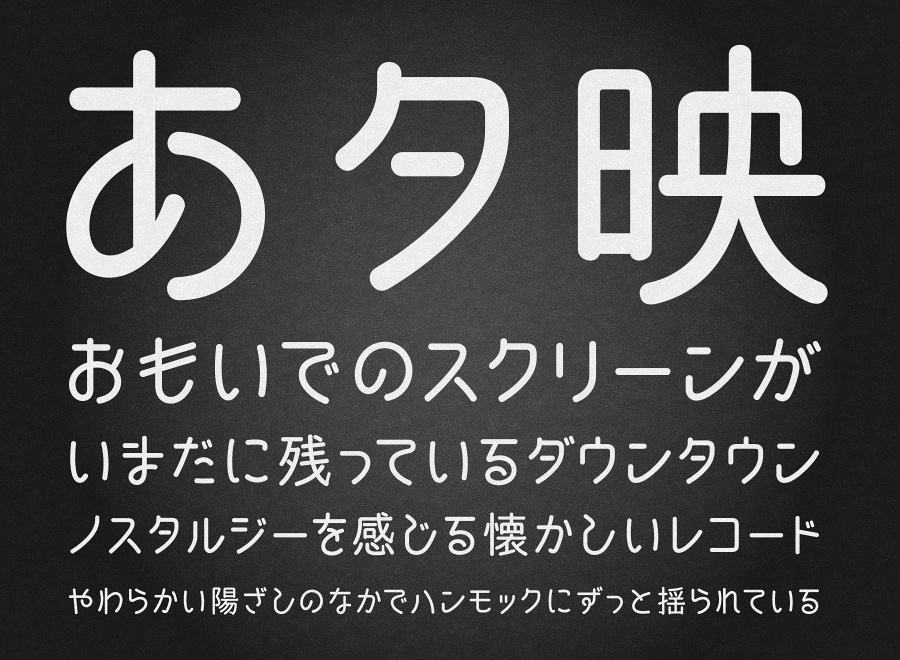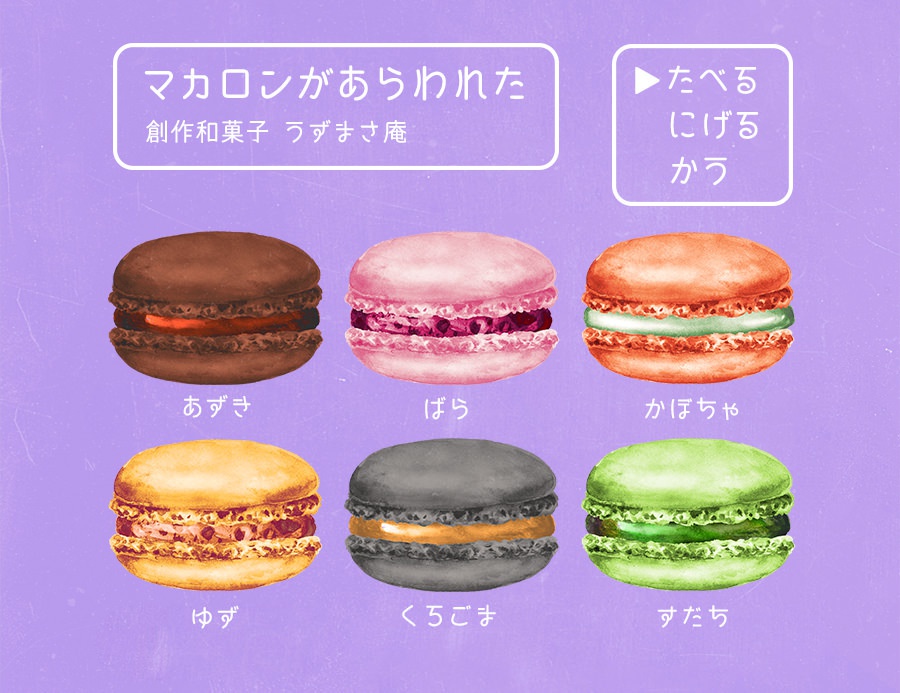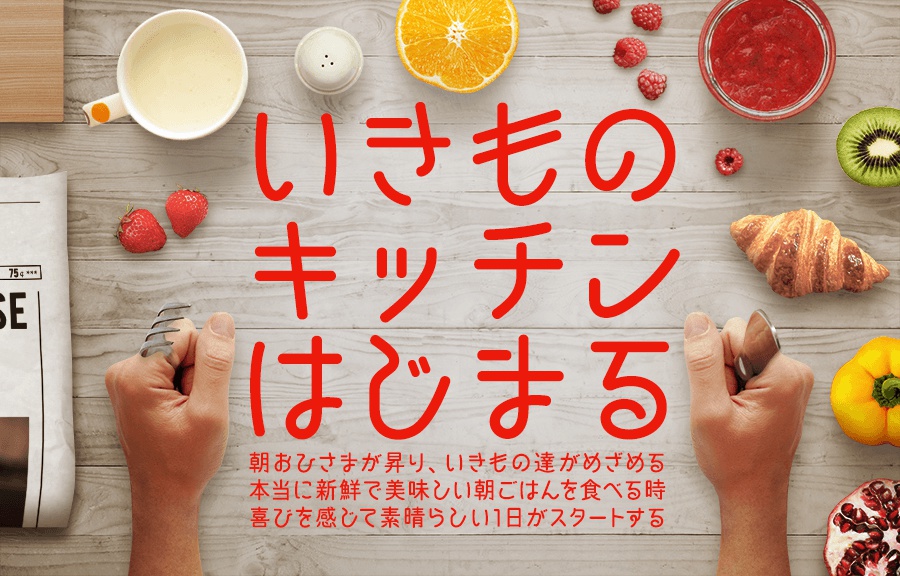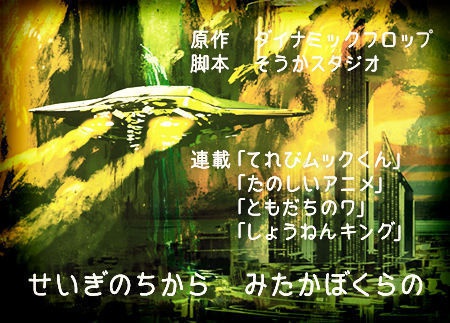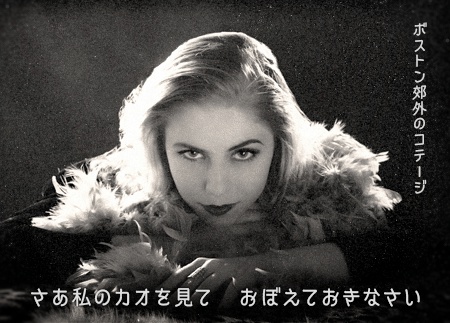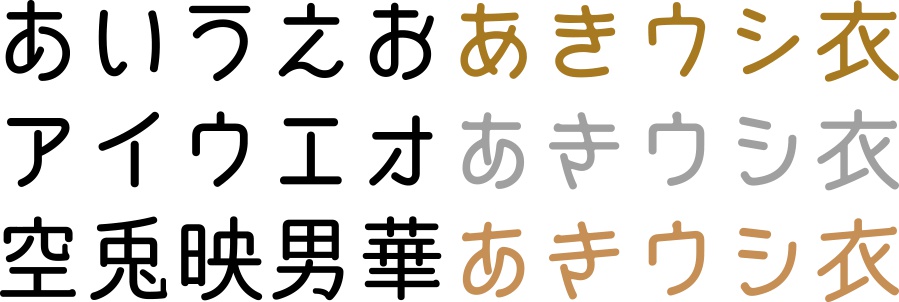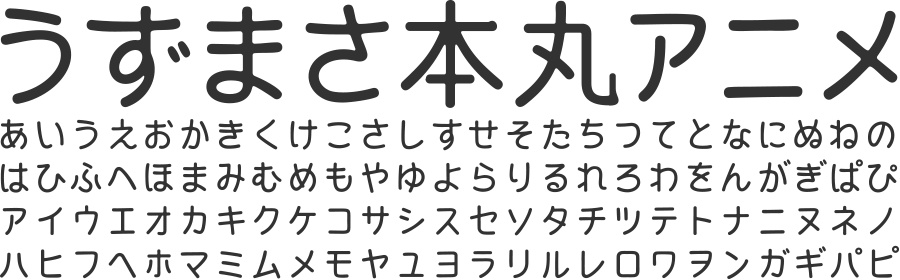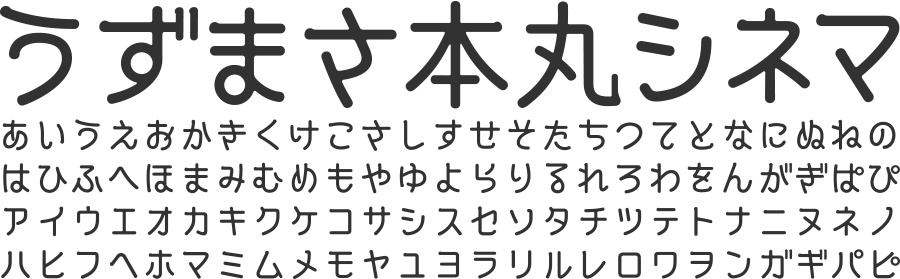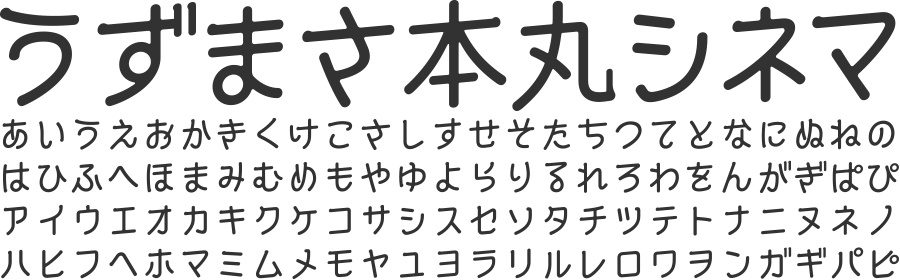
うずまさ本丸ゴシック - 5フォントSET
京都市右京区太秦(うずまさ)をイメージした丸ゴシック体。京都を中心とした関西系の時代劇の無声映画時代(〜1920年代)の手書きの字幕文字をヒントに、フォントとして現代に甦らせました。暖かみのある書体が印象深いデザインを可能にします。 古い昭和アニメのテロップ風の「うずまさ本丸ゴシックアニメ」、普通の字幕文字風の「うずまさ本丸ゴシック-シネマ」、縦に斜体の字幕文字「うずまさ本丸ゴシック-シネマ斜体」の3書体も入っています。さらに、うずまさ本丸ゴシックの個性を少し減らした「うずまさ本丸ゴシック-ノーマル」も付属。 収録フォント(5書体) うずまさ本丸ゴシック(レギュラー)、うずまさ本丸ゴシックアニメ、シネマ、シネマ斜体、ノーマル(4書体) 動作環境 Mac:システム/OS X対応(10.x)〜最新のOS X Windows:OS/日本語版Windows2000、XP、VISTA、Windows7〜11以降 フォント形式:OpenTypeフォント、TrueTypeフォント 収録文字数について 収録文字数4,072文字(第一水準2965文字+第二水準460文字+ひらがな.カタカナ.約物.記号.アルファベット等647文字) 安心して使えるロイヤリティフリーの書体 あらゆる商用・デザイン用途(印刷物・ゲーム・アプリ・映像・動画・ロゴ・同人作品)に使用できる、商用申請の必要のないロイヤリティフリーの書体になります。文字の加工・変形も可能です。ご安心ください。